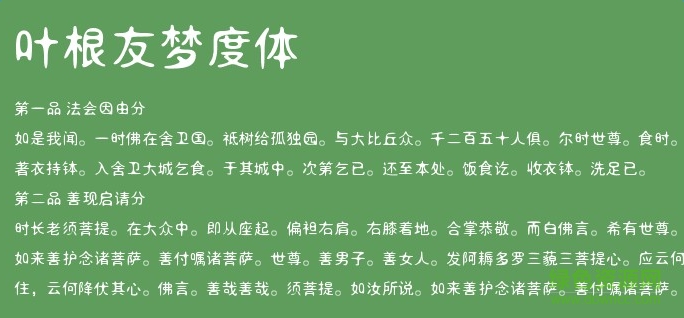
葉根友夢度體是一款非常有特色的字體,這款字體字形非常耐看,字如其名,深受廣大用戶的喜愛,這里還有更多優(yōu)美好看的字體任你選擇,喜歡的朋友不妨來綠色資源網(wǎng)下載吧!
葉根友夢度體是一款圓潤而又富有詩意的字體,猶如夢境情景,取名夢度體。
這款字體猶如夢境情景,給人一種夢境般的感覺,字體的棱角圓潤,透露出一種集浪漫又可愛的氣息,非常耐看,給人的整體效果比較優(yōu)美,感興趣的話可以來綠色資源網(wǎng)下載試試喲!